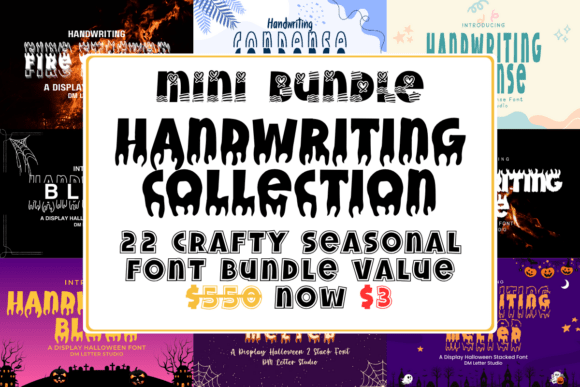
Handwriting Collection Font Bundle
Si vous recherchez des ressources de haute qualité comme Handwriting Collection Font Bundle, ce pack premium est un choix fantastique pour vos projets créatifs.
Conçu avec précision, Handwriting Collection Font Bundle offre des vecteurs nets, une typographie fluide et une licence commerciale pour une tranquillité d'esprit.
Que vous créiez des produits POD (impression à la demande), des invitations de mariage ou des visuels pour les réseaux sociaux, Handwriting Collection Font Bundle est un choix idéal.